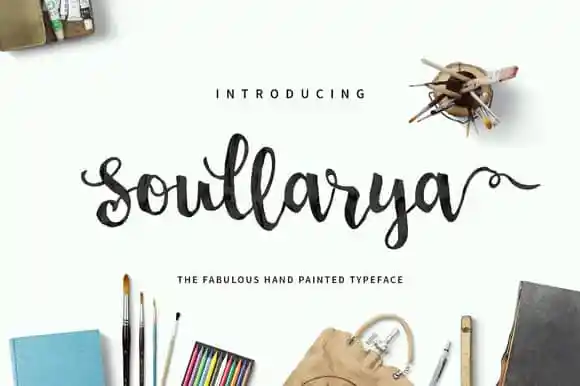
Soullarya Script Font – Download Grátis
Soullarya Script Font é uma fonte brush script que inspira-se no estilo livre de letra com um pincel, ideal para aplicações modernas e criativas. Criada por Mustaqim Ibra, esta fonte premium é agora gratuita para download na CreativeMarket. Soullarya se destaca pela sua aparência ousada e atrativa, oferecendo uma variedade de alternativas para letras maiúsculas e minúsculas. Suportando várias línguas internacionais, a fonte traz um toque autêntico e original à qualquer design gráfico em que for usada, seja para criar logos com letra com pincel, cartões de cumprimentos ou convites de casamento. Soullarya é perfeita para quem busca expressar personalidade e estilo em seus projetos de arte digital. Experimente e descubra a versatilidade desta fonte que vai deixá-lo impressionado por sua facilidade de uso e beleza única.